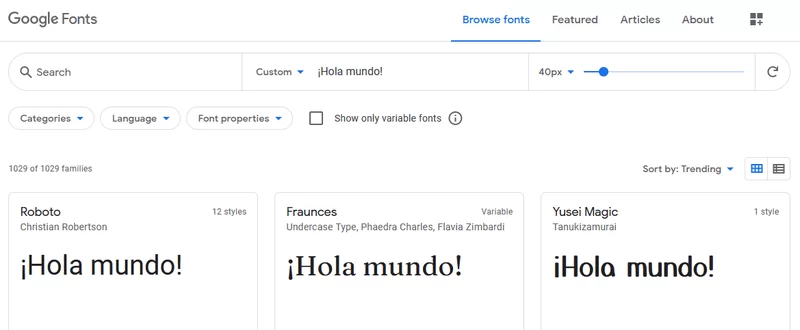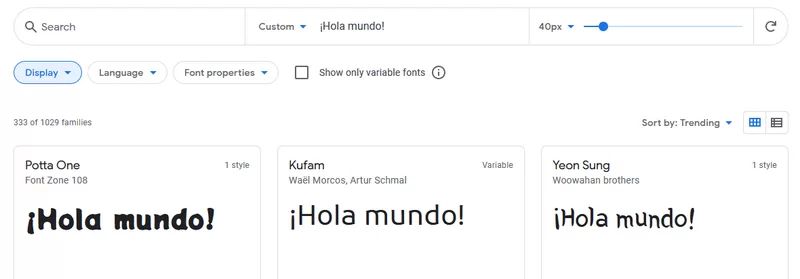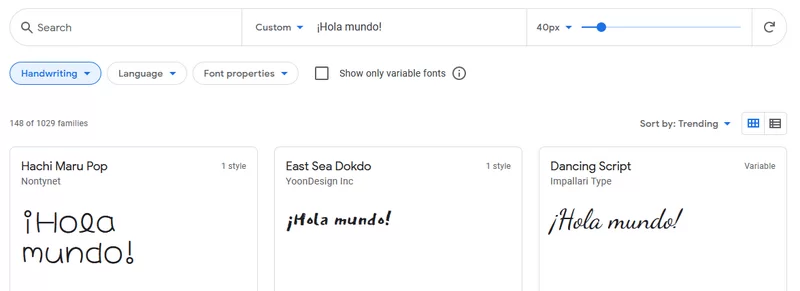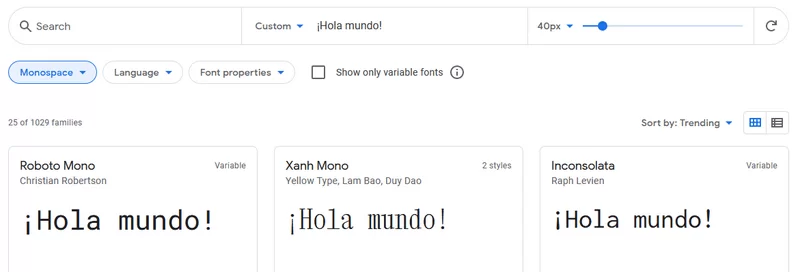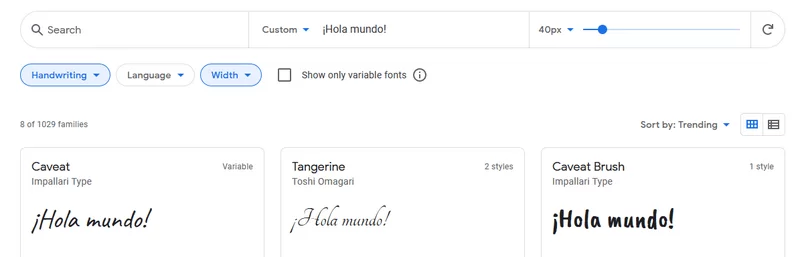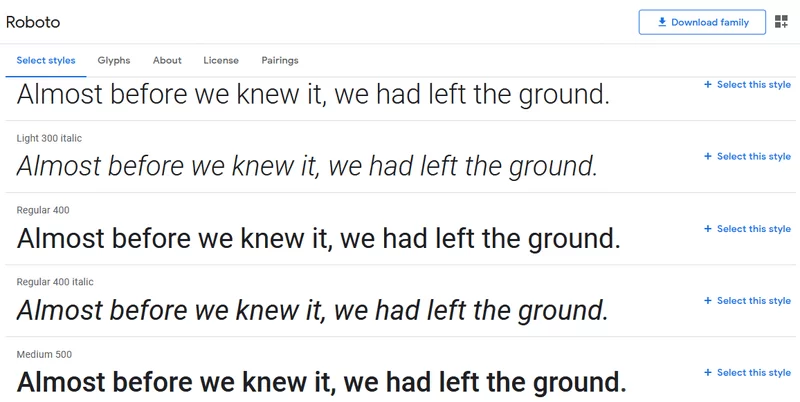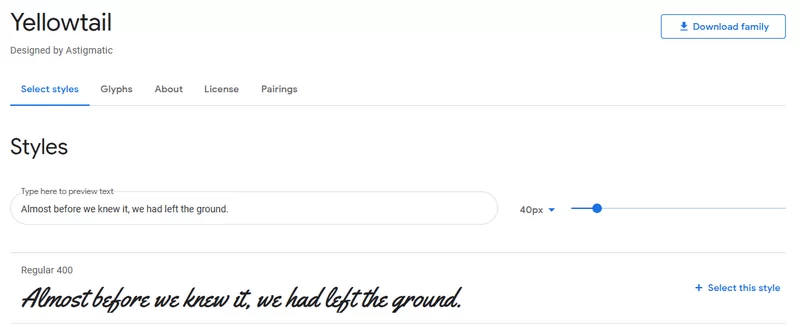
Una imagen vale más que mil palabras. Pero si esas palabras tienen la tipografía correcta, conseguirás el impacto de una gran imagen.
Las fuentes de Google son un conjunto de tipografías que han agrupado y puesto disponible para todo el mundo.
Qué son las Web Fonts
Durante muchos años, en el diseño web solo se podían usar unas fuentes tipográficas, llamadas “fuentes seguras”.
Esto era debido a que, para que se visualizara correctamente una fuente en un ordenador mientras navegabas por Internet, el usuario debía tener instalada en su dispositivo esa tipografía.
Si no, no podía ver ese tipo de letra y la maquetación de la web se “descolocaba”.
Esto pasa hoy en día en la aplicación, por ejemplo, de PowerPoint. Si quieres utilizar una fuente que no viene instalada por defecto, debes instalarla tú mismo.
Este problema se solucionó con la llegada de las “Web Fonts”. Estas son tipografías muy variadas, que se almacenan en el servidor (en vez de tener que descargarlas en cada dispositivo), por lo que, cuando carga una página web, se descargan junto a las fotos y al texto.
Además, las fuentes de Google Fonts están comprimidas para que se descarguen en tu dispositivo de una forma rápida y sencilla.
Estas tipografías se mantienen almacenadas en la caché de tu dispositivo; si vuelves a entrar en una página con estas fuentes no se tienen que volver a descargar.
Qué es Google Fonts o Google Web Fonts
Google Fonts, conocido anteriormente como “Google Web Fonts”, es un catálogo o repositorio de estas fuentes con multitud de estilos tipográficos; completamente gratuito y libre de derechos.
En la actualidad hay más de 900 familias, cada una de éstas con variantes en cuanto al grosor de la letra o el estilo cursiva.
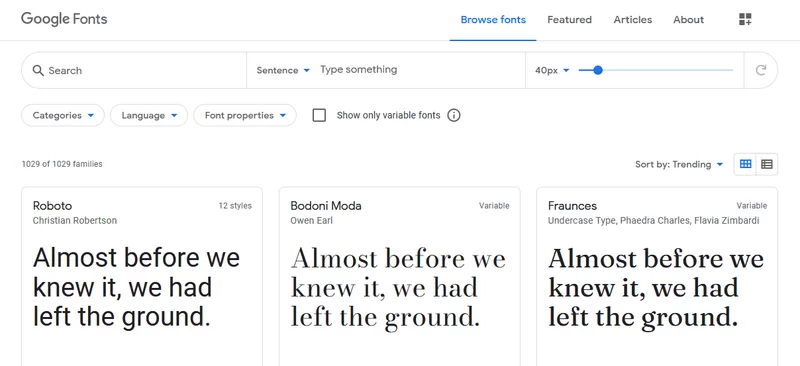
Por qué utilizar las fuentes de Google Fonts
Aunque las fuentes de Google nacieran en gran parte para dar solución al problema que hemos visto del diseño web, en la actualidad se utilizan para cualquier tipo de diseño, como el de presentaciones de PowerPoint y plantilla de documentos en Word.
Por lo que, aunque no seas diseñador, las fuentes de Google tienen muchas ventajas para ti.
Conseguirás diseños originales y elegantes en tus presentaciones de PowerPoint
Como ya hemos hablado, estas fuentes las puedes utilizar en cualquiera de las aplicaciones de Office, como PowerPoint, y conseguir diseños increíbles.
Dependiendo de la temática que tengas, podrán servirte unas u otras; pero entre las 900 que tienes disponibles seguro que encuentras la combinación perfecta.
Y es que, es muy recomendable utilizar entre dos y tres fuentes para cada diseño.
De esta forma, conseguirás que la gente perciba tu presentación como mucho más trabajada y lograda, además de quedar mucho más estético.
Puedes utilizar su catálogo como inspiración
Si estás un poco perdido y no sabes que fuentes quedarán mejor en tu web o presentación, la página principal de Google Fonts puede servirte de inspiración.
En una de las opciones que hay al principio puedes escribir una palabra o texto para ver cómo queda con cada fuente.
También puedes filtrar el tipo de letra que buscas: desde una con mucho grosor hasta una que imite a la caligrafía.
Por ejemplo, para buscar una fuente con más grosor de lo habitual, haz clic en “Font Properties” y luego marca la casilla de “Thickness”. Al deslizar el cursor por la barra, irás filtrando las tipografías.
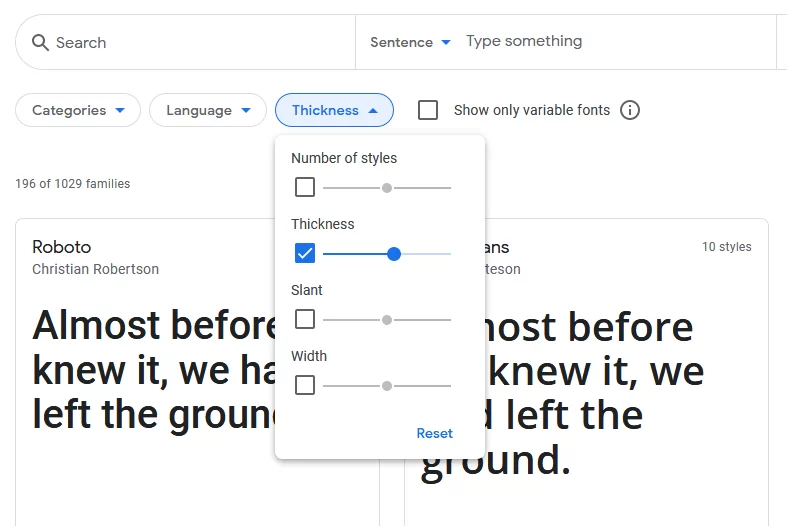
Si estás buscando combinaciones de letras que puedan quedar bonitas, ¡echa un vistazo al último apartado de este post!
Son muy fáciles de usar: descarga, instala y ¡listo!
Para utilizar una fuente de Google tan solo deberás elegirla en su página principal, descargarla e instalarla en tu ordenador.
En el apartado siguiente vemos cada uno de esos pasos explicados detalladamente.
Permiten diseños web “responsive”
Un diseño responsive es aquel en el que los elementos de la página web (texto, imágenes, columnas etc) se adaptan a cualquier tipo de pantalla (móvil, ordenador o Tablet).
Las fuentes de Google están diseñadas para cualquier tipo de dispositivo y navegador, por lo que, si eres diseñador web, no tendrás ningún problema a la hora de utilizarla.
Cómo usar Google Fonts
Sí todo lo que hemos visto hasta ahora te ha convencido y quieres empezar a utilizar las cuentas de Google en tus diseños, debes ir a su página principal: www.googlefonts.com
En la parte de arriba hay una barra buscadora, por si ya conoces el nombre de una fuente y quieres buscarla.
Hola
la verdad es que es muy interesante el tema de las Google Fonts para que la imagen de la web tenga un buena presencia.